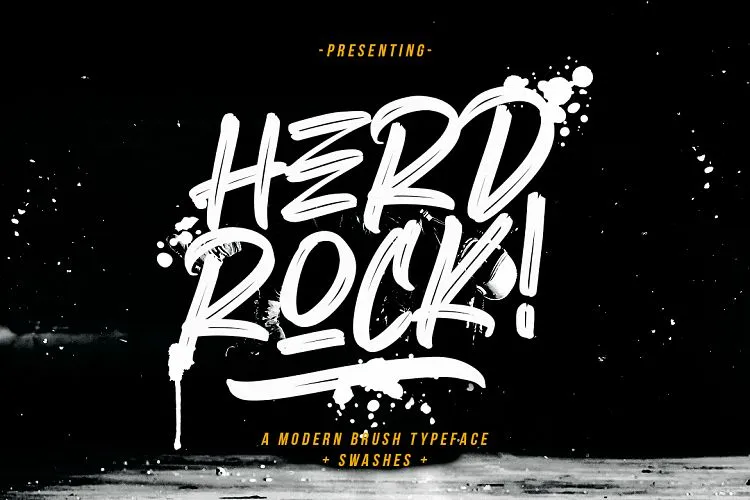
Bem-vindos à categoria de Script Fonts! Hoje, apresentamos Herdrock Brush Font, uma moderna tipografia feita sob a inspiração de canetas esferográficas. Esta criação do designer 0001themes é perfeita para quem deseja dar um toque cool e futurista às marcas ou publicações digitais. Herdrock Brush é um font super-hiper-blastado, repleto da estriatura moderna e de um estilo que promete deixar seus trabalhos ainda mais atraentes. Essa tipografia é perfeita para os criativos que desejam dar uma cara jovial e inovadora aos seus projetos digitais. Com Herdrock Brush Font, você pode criar designs gráficos vibrantes sem sair da sua cadeira de trabalho. Seja em um site ou aplicativo, ele trará um toque único à sua marca digital. Essa font, além de sua versão regular, também oferece uma opção com efeitos mais marcados – o que permite ainda maior personalização. Descubra como Herdrock Brush pode transformar a aparência da sua próxima publicação digital!